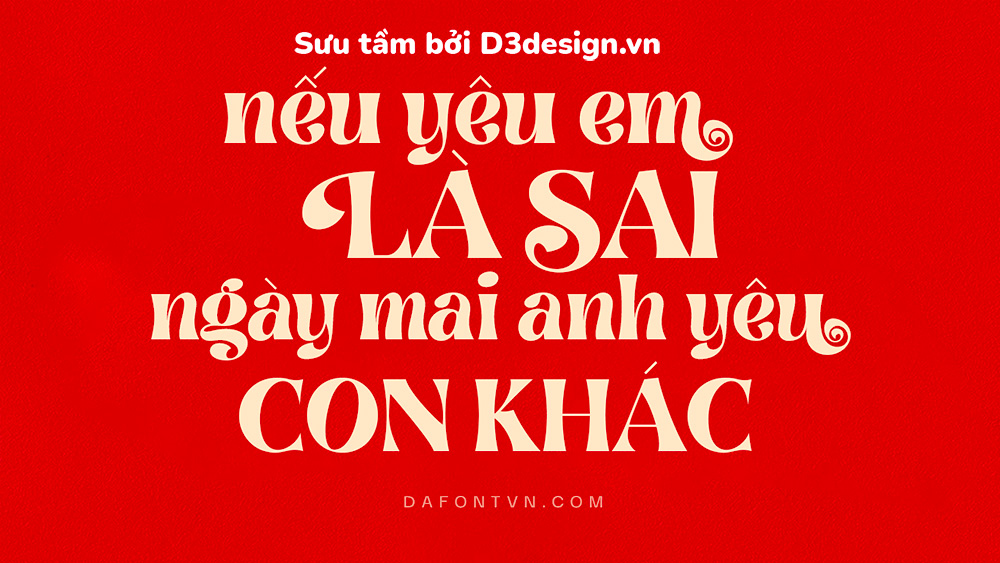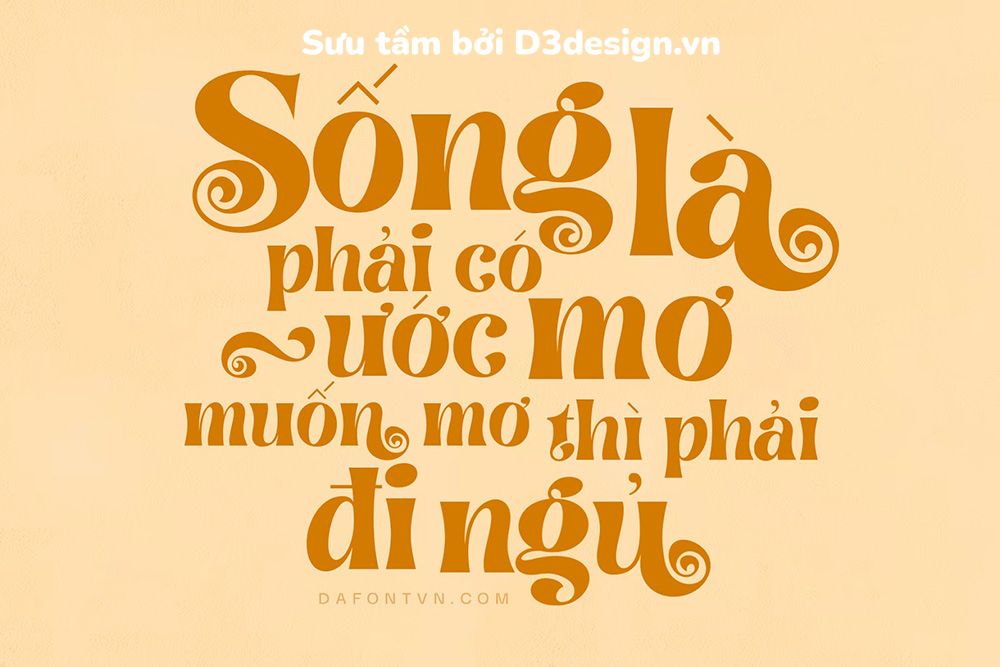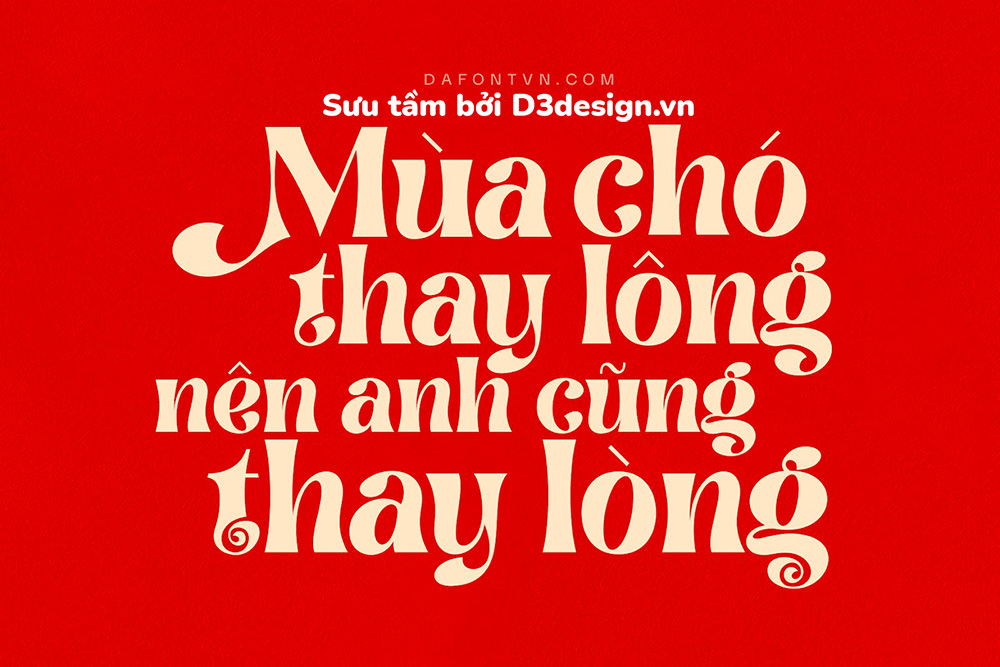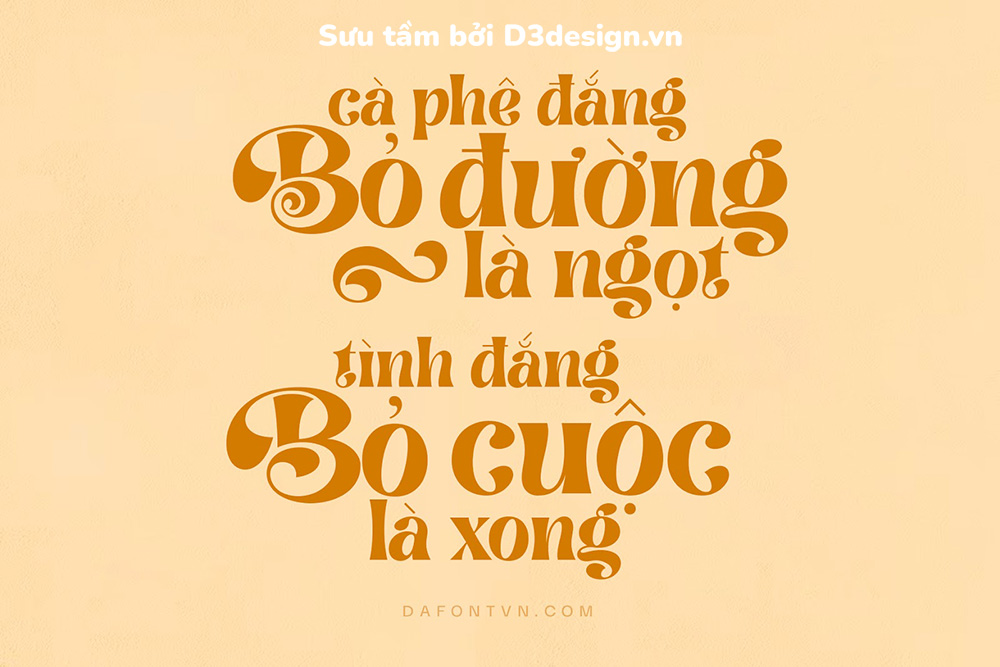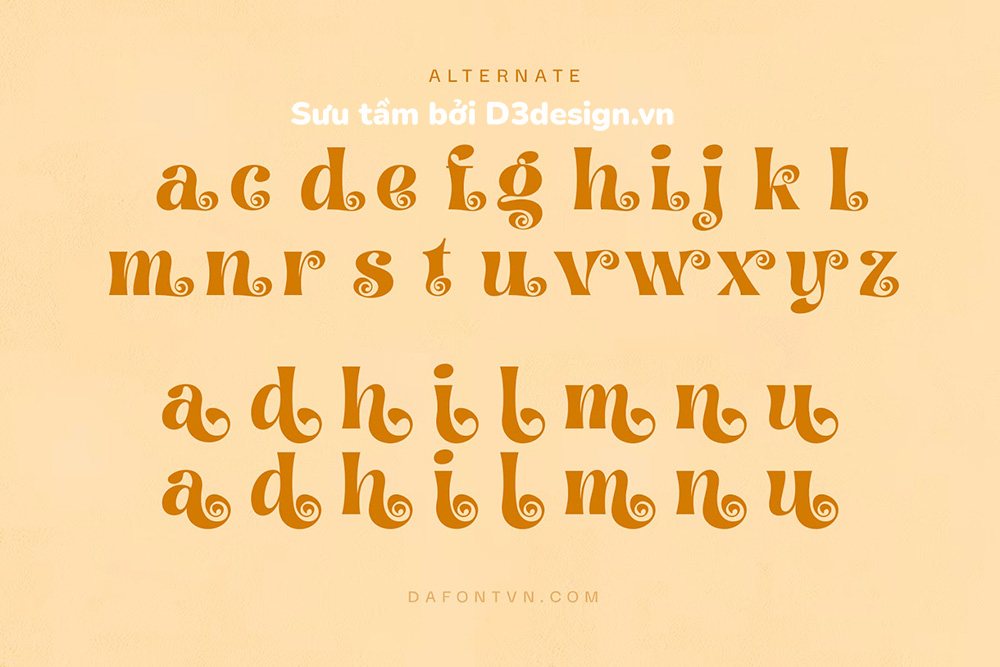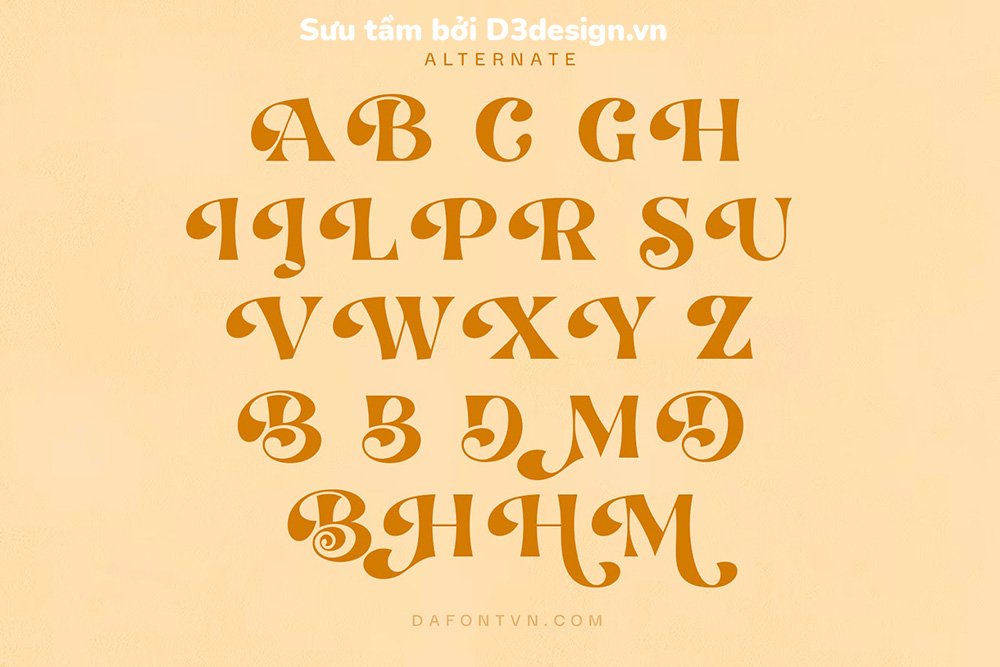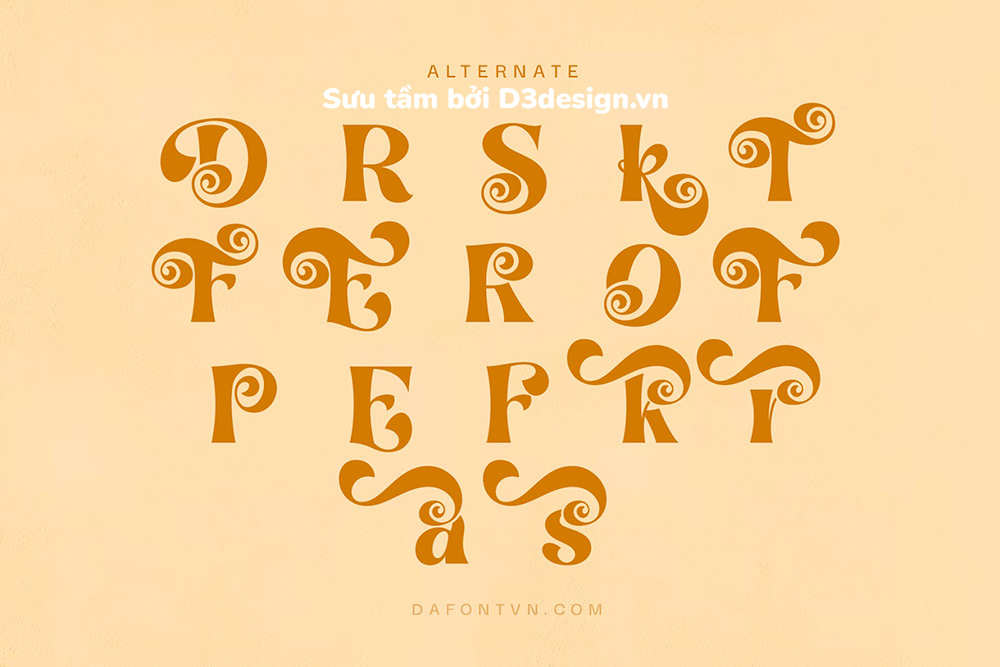
Font Việt Hóa - Brasika Display Mang Phong Cách Vui Nhộn Và Ấn Tượng
Font Brasika Display Việt hóa được thiết kế linh hoạt, với các nét chữ có phần xoáy mềm mại và dễ thương, dễ dàng để sử dụng cho hầu hết các thiết kế, đặc biệt cần đến một font chữ hiển thị đẹp mắt.
Bạn có thể sử dụng font này trong nhiều thiết kế như logo, thương hiệu, lời mời, thiệp mừng, bìa sách, typography hay bất kỳ thiết kế nào khác cần đến 1 kiểu font lạ mắt, ấn tượng và phong cách. Ngoài ra Brasika, có rất nhiều glyph mà bạn có thể áp dụng cho các thiết kế của mình để tạo ra những tác phẩm xịn xò hơn.
Font được việt hóa đầy đủ, kerning và chỉnh sửa lại đôi chút dấu cũng như tối ưu để sử dụng dễ dàng trên bất kỳ phần mềm thiết kế nào. Bạn có thể sử dụng các glyph trên Photoshop, AI hoặc các phần mềm khác có hỗ trợ OpenType.